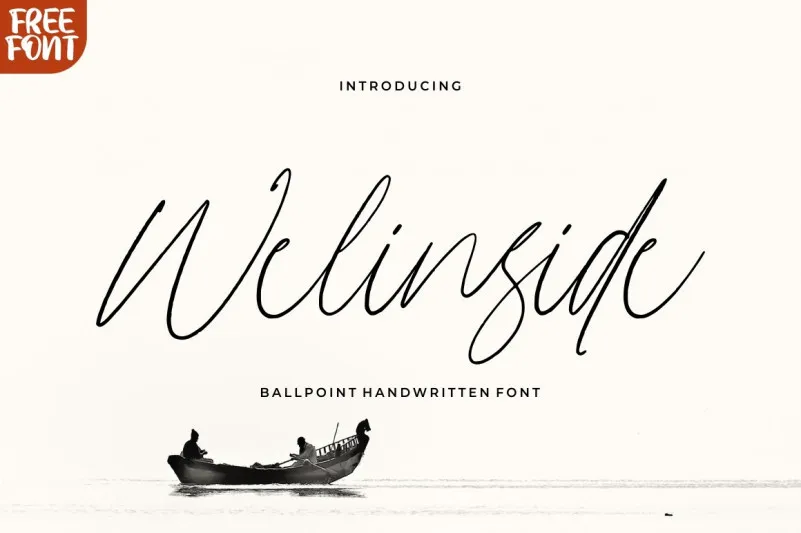
Welinside Script Font – Fonte Grátis
Welinside Script Font
Olá! Se você está procurando uma nova fonte para dar ao seu próximo projeto uma pitada especial de sofisticação e autenticidade, a Welinside Script pode ser exatamente aquilo que você precisa. Essa fonte foi inspirada nas grifes luxuosas e na natureza da própria escrita humana, garantindo um visual único e singular. Projetada pelo estúdio Good Java Studio, ela é perfeitamente adaptável para variedades de usos, desde cartões de convite até ações sociais, blogs pessoais ou aplicações comerciais. Com uma característica natural da própria escrita humana, a Welinside Script destaca-se não apenas por sua beleza estética, mas também pela capacidade de tornar seus projetos ainda mais autênticos e únicos. Se você está em busca de um recurso gráfico que respeite tanto o cuidado quanto a criatividade, esta é a fonte certa para você. Descubra por si mesmo a diferença que ela pode fazer!